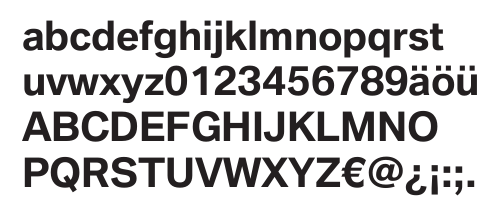
Hübsche schlichte Schrift von BMW Drive Now
kann mir jemand sagen, welche schlichte Schrift das hier ist?[
Kommt vielleicht irgendwas von den üblichen Verdächtigen nahe?
Die Hausschrift von BMW, BMW Type, ist es nicht. Hier eine Abbildung davon (Klick führt zu PDF-Datei zur Schrift):
Die Schrift ist aber sehr ähnlich; vielleicht wurde die DriveNow-Marke auf ihrer Grundlage entwickelt?
Ähnlich sind außerdem die Akzidenz Grotesk und die FF Dagny.
Die News ist sehr ähnlich, das Original-r ist aber sehr speziell.